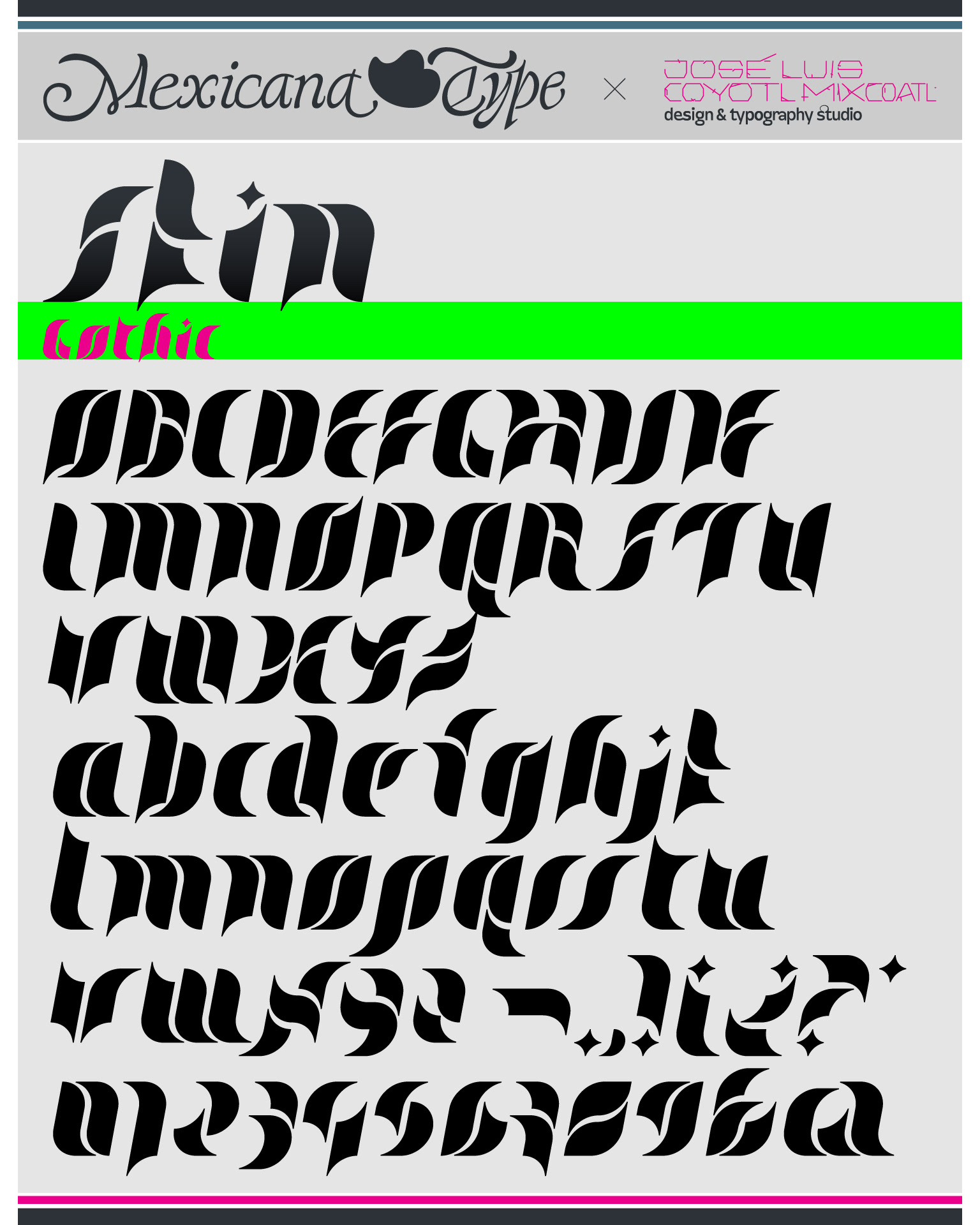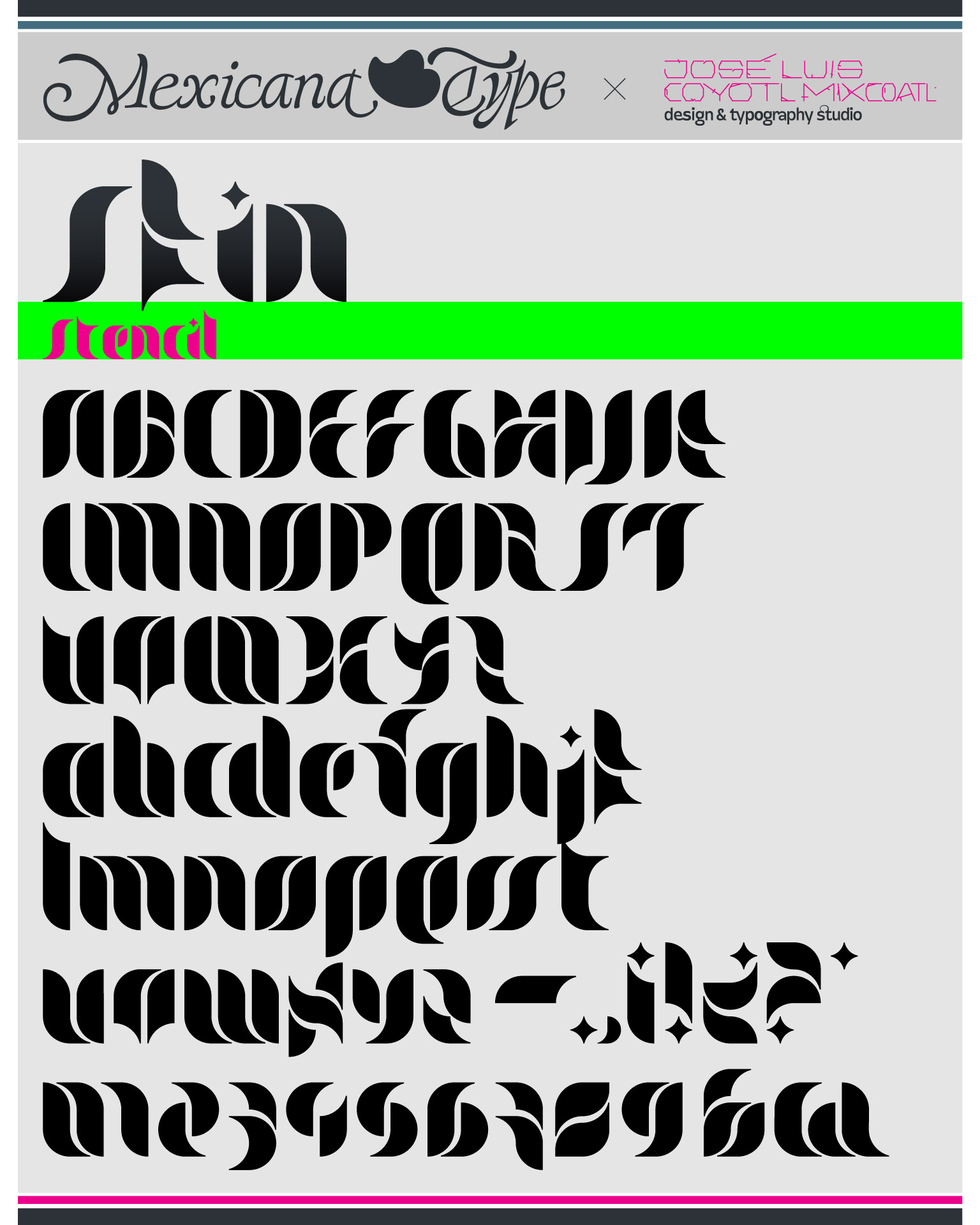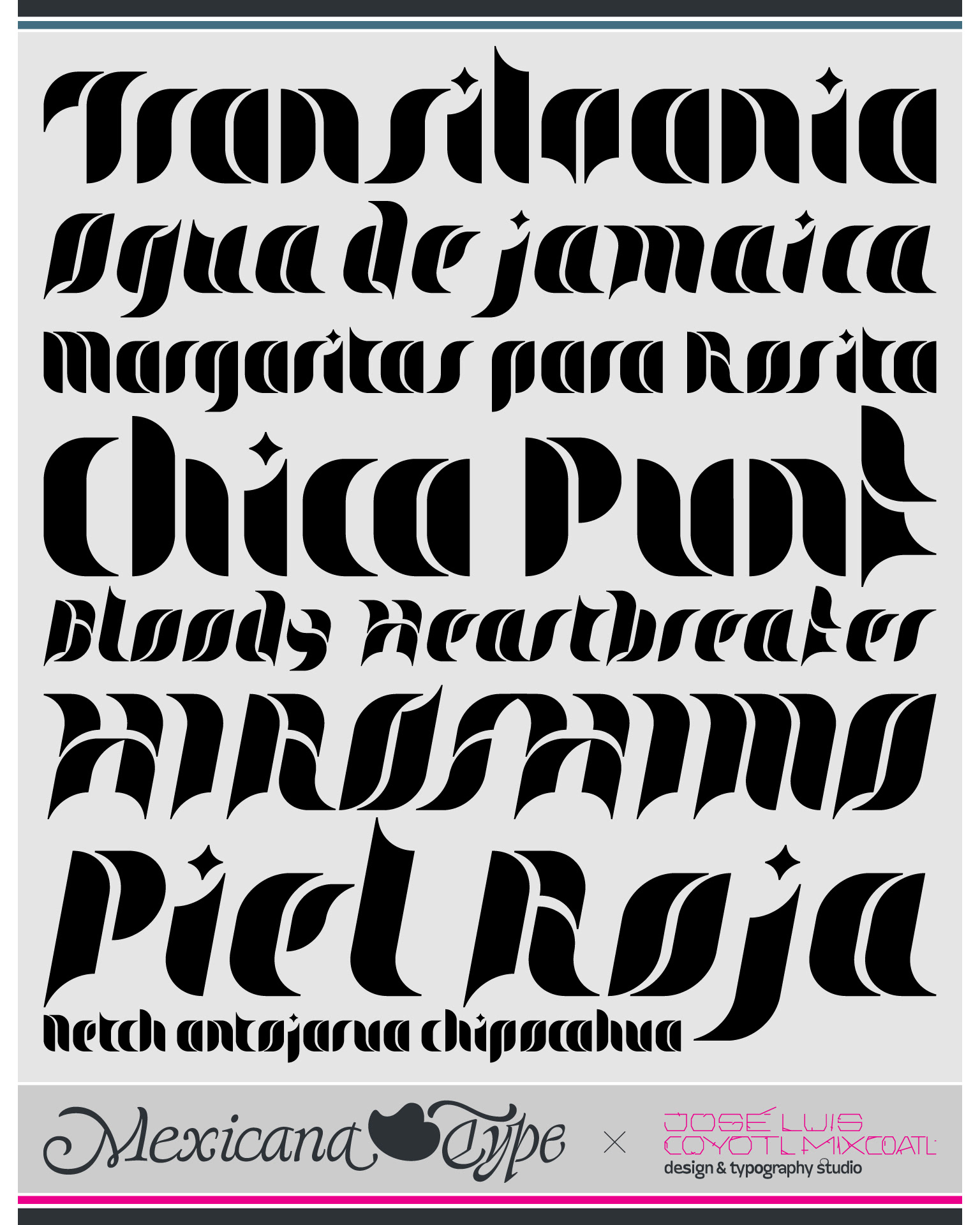
MxT Skin es una tipografía desarrollada como un stencil con elementos que remiten a las letras góticas, pero con un sentido mucho más abstracto y modular buscando simplicidad pero tambien un estilo muy singular y en sus formas, compactas y llenas de juegos de formas, con terminaciones agudas y trazos gruesos y sólidos.
Las formas de cada caracter están construídas con una serie de elementos redondeados, en espuela y módulos cuadrados, aplicadas en sus dos versiones: MxT Skin Gothic y MxT Skin Stencil. Si bien son tipografías con cierto nivel de dificultad para ser leídos, su estética generan texturas tipográficas únicas.